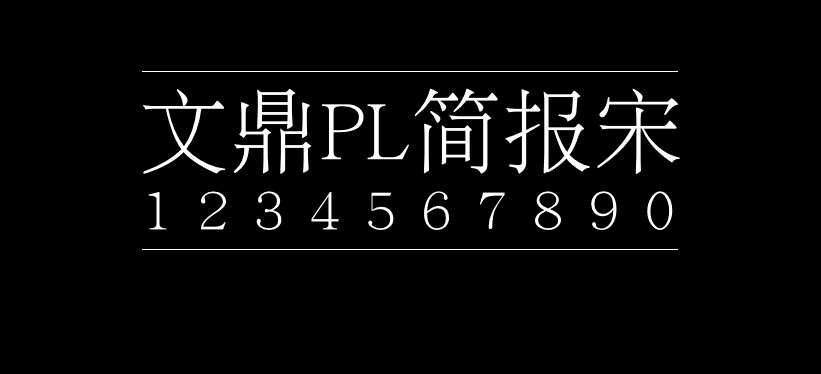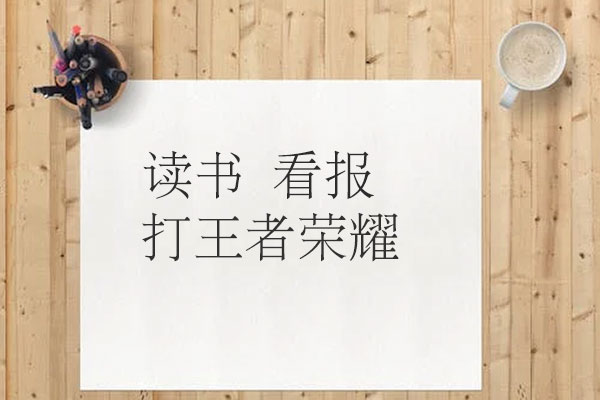
文鼎PL简报宋
文鼎PL简报宋是Linux操作系统上最早的高质量开源中文字体,是文鼎科技于免费提供捐赠予自由软件社区的一套宋体字体,这套宋体字体字形比较纤细,比较适合文字排版阅读、优雅古风的设计。
字体名称中的“PL”并不是指漂亮,而是代表这款字体是公众授权Public License。文鼎科技共免费提供了4套公众授权的字体,这四款字体分别是:文鼎PL简中楷、文鼎PL中楷体(BIG5)、文鼎PL细上海宋、文鼎简报宋,需要的可以在本站搜索下“文鼎”即可获得。